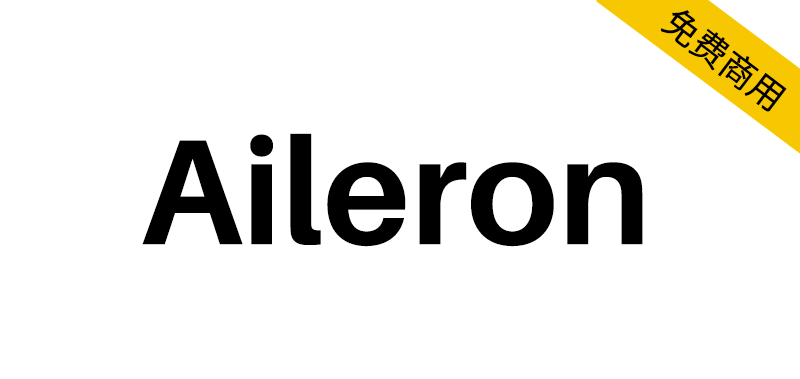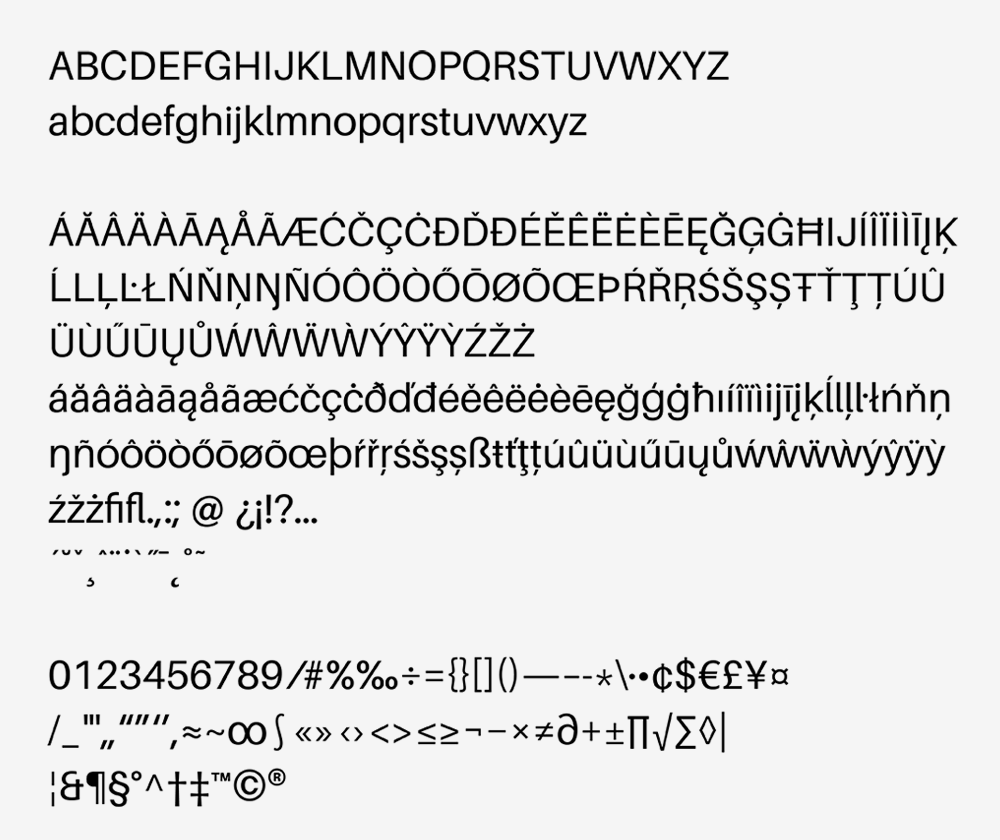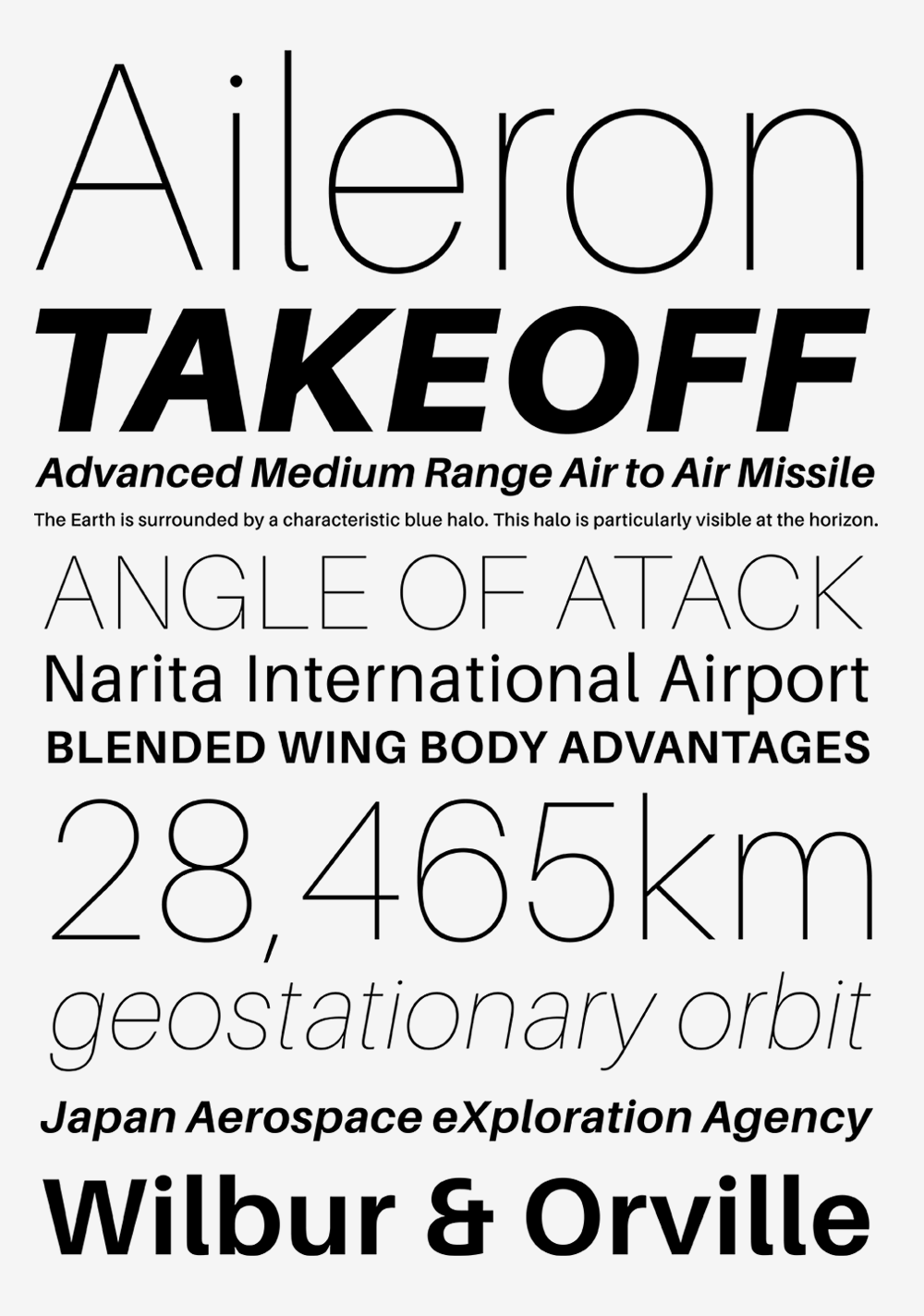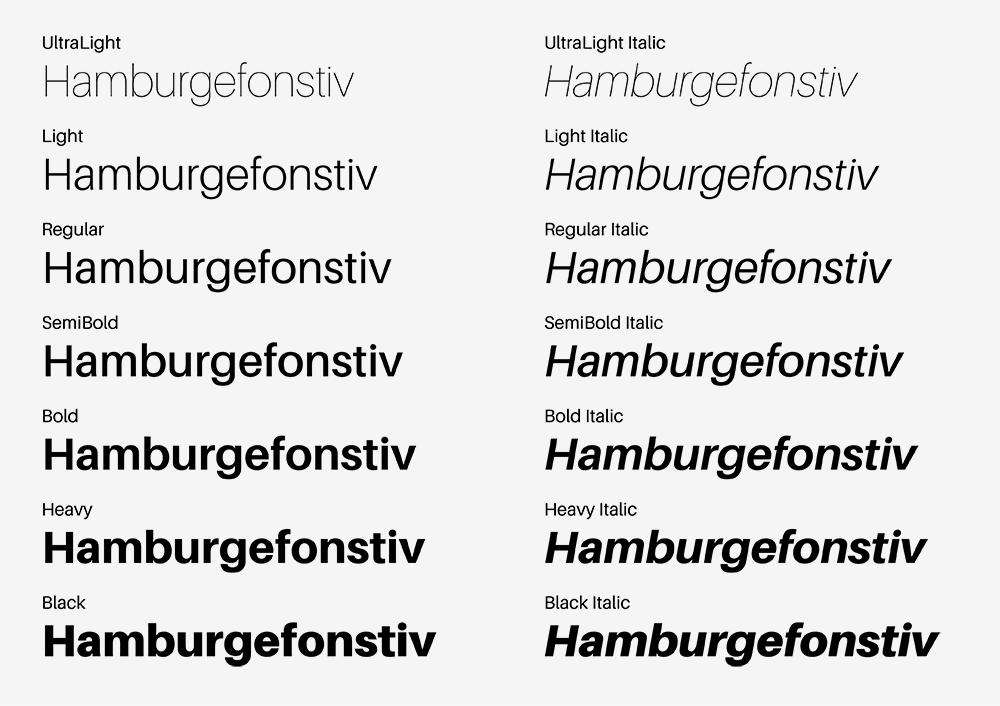
Aileron 是一种无衬线字体,基于 Helvetica 等新怪诞字体,并添加了我自己的解释。
作为对文字的调整,字母之间的间距稍微变宽,小写字母“L”的末端已弯曲,以便更容易将其与大写字母“I”区分开。
另外,“i”、“j”、句号等圆点都被做成了圆形,弯曲的部分也被处理成类似回旋曲线的形状,整体给人一种柔和的感觉。在设计上,它与 Helvetica 类似,但在概念上,它与 Univers 更相似。
此外,这是我们第一次准备斜体版本的点冒号字体。基本上,它是机械倾斜的,但已经进行了视觉修正,因此不会感到奇怪。
利用多重主控的优势,提供从超轻到黑色的 8 个重量级别。我认为它可以用于多种情况。
Aileronは、Helveticaをはじめとするネオグロテスクに分類される書体を参考に、自分なりの解釈を追加しまとめたサンセリフフォントです。
本文向けの調整として若干字間を広めにし、大文字アイ「I」との識別をしやすくするため、小文字エル「l」の末端部分をカーブさせたデザインにしています。
ほか、「i」や「j」やピリオドなどのドット部分を円形に、曲線部分にクロソイド曲線を意識した処理を施す事で、全体的に柔らかい印象が出るようにしました。デザイン的にはHelveticaに近いですが、コンセプト的にはむしろUniversに近いものになっています。
また、今回ドットコロンのフォントとしてはじめてイタリック体を用意しています。基本は機械的に傾けたものですが、違和感のないように視覚補正を施しました。
マルチプルマスターを生かし、ウェイトはUltraLightからBlackまで8段階を用意。広い場面で使っていただけると思っています。